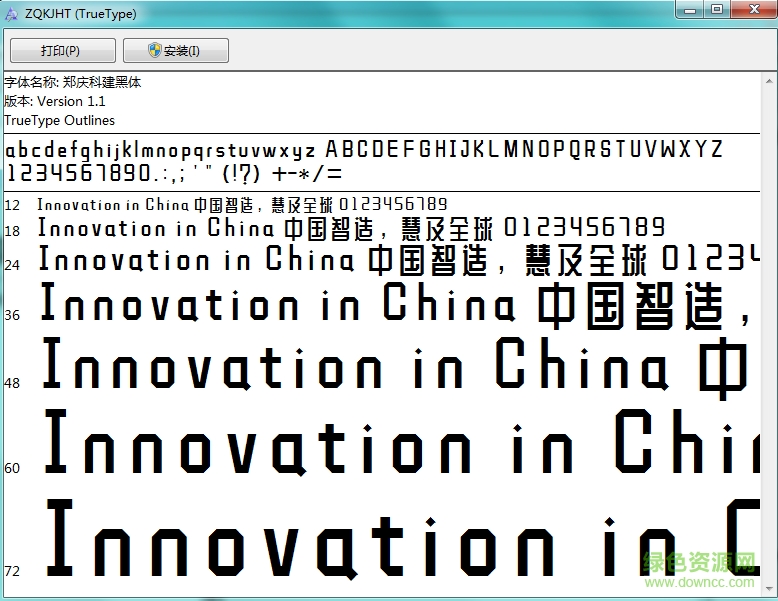
鄭慶科建黑體(非商用)
鄭慶科建黑體是一款非商用的中文字體,字體有著極規(guī)整的四方形裝,在部分筆畫處又有著三角形的缺口,很有幾何的美感,喜歡的朋友來綠色資源網(wǎng)免費下載吧!
鄭慶科字體介紹
建黑體由鄭慶科所創(chuàng),字體完整不缺字,支持繁簡體輸入,端正大氣的造型很容易獲得設(shè)計師的好感,廣泛應(yīng)用于平面設(shè)計、海報設(shè)計、LOGO設(shè)計等領(lǐng)域。
鄭慶科建黑體
作者有話說
自2013年7月到2016年2月,終于把建黑體6763個漢字補全(GB2312標準),拖了很久,說真的,很累,很枯燥。